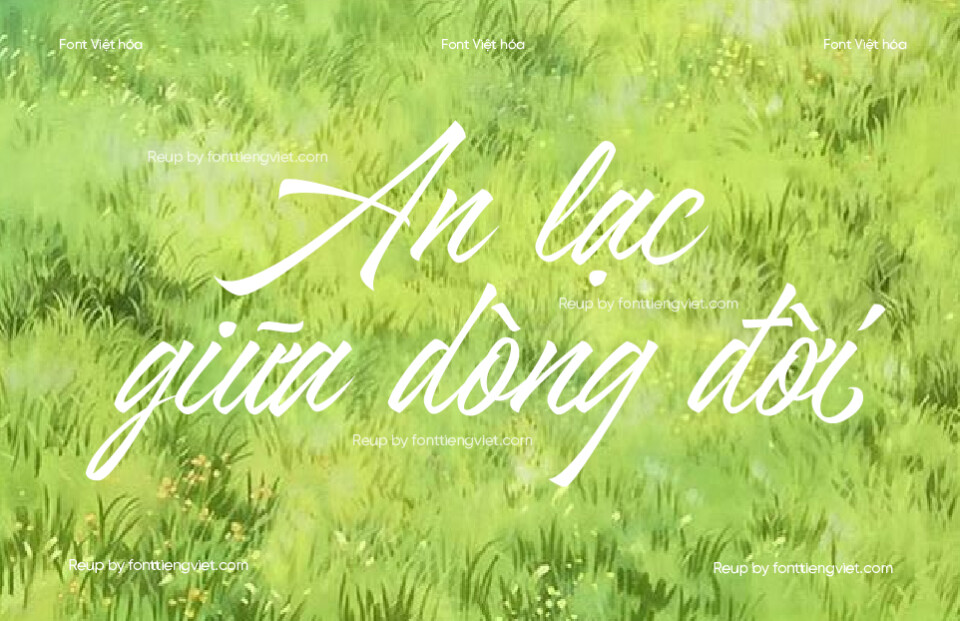
Khám Phá Nét Đẹp Tinh Tế Của Font Việt hóa UTM Azkia Trong Thiết Kế
Trong thế giới của typography và thiết kế đồ họa, việc lựa chọn một bộ phông chữ phù hợp có thể quyết định đến sự thành công của toàn bộ dự án. Font Chữ không chỉ là công cụ truyền tải thông điệp mà còn là linh hồn tạo nên phong cách. Trong số các lựa chọn đa dạng hiện nay, Font Việt hóa UTM Azkia nổi lên như một lựa chọn hàng đầu cho những ai tìm kiếm sự kết hợp giữa nét đẹp mềm mại, cổ điển nhưng vẫn rất hiện đại. Được phát triển và Việt hóa hoàn chỉnh, UTM Azkia đã nhanh chóng chiếm được cảm tình của cộng đồng designer Việt Nam, đặc biệt trong các lĩnh vực như thiết kế thiệp cưới, bao bì sản phẩm cao cấp, và nhận diện thương hiệu sang trọng. Bộ font này mang đến sự trau chuốt, tỉ mỉ mà ít phông chữ nào có thể sánh được.
Giới Thiệu Chi Tiết Về Font Việt hóa UTM Azkia và Đặc Điểm Nổi Bật
Font Việt hóa UTM Azkia thuộc nhóm font script hoặc brush script, nổi bật với các nét uốn lượn mềm mại, dứt khoát mô phỏng chữ viết tay thư pháp. Sự Việt hóa chuẩn mực là yếu tố then chốt giúp font này trở nên phổ biến, đảm bảo rằng mọi ký tự tiếng Việt, bao gồm các dấu câu và chữ cái có dấu, đều được hiển thị một cách hoàn hảo và tự nhiên nhất. Điều này giải quyết triệt để vấn đề lỗi phông thường gặp khi sử dụng các font quốc tế chưa được tối ưu cho tiếng Việt.
Điểm mạnh của UTM Azkia không chỉ nằm ở tính thẩm mỹ cao mà còn ở sự đa dạng trong cách thể hiện cảm xúc. Nó có thể được sử dụng để truyền tải sự lãng mạn, sự tinh tế, hoặc thậm chí là một chút phá cách, tùy thuộc vào cách bạn kết hợp nó với các yếu tố thiết kế khác. Các nét nối liền mạch và độ dày mỏng linh hoạt của nét chữ tạo nên một cảm giác rất “thủ công” và chân thực.
Khác Biệt Giữa UTM Azkia Gốc và Bản Việt Hóa
Bản gốc Azkia là một font chữ tuyệt đẹp, nhưng để sử dụng hiệu quả trong môi trường tiếng Việt, việc “Việt hóa” là bắt buộc. Nhóm Việt hóa UTM đã thực hiện công việc tỉ mỉ này, không chỉ thêm các ký tự dấu mà còn tinh chỉnh kerning và spacing để đảm bảo sự hài hòa tổng thể. Nhờ quá trình này, người dùng hoàn toàn có thể yên tâm sử dụng font này cho các tài liệu học tập, sách báo, hay các ấn phẩm in ấn đòi hỏi sự chính xác cao về mặt ngôn ngữ.
Việc sử dụng các font chữ đã được Việt hóa như Azkia giúp các bạn học sinh, sinh viên trong quá trình làm tiểu luận, thiết kế bài thuyết trình hoặc làm các dự án sáng tạo cá nhân có được sản phẩm chuyên nghiệp hơn. Thay vì dùng các font phổ thông, Azkia mang lại dấu ấn cá nhân rõ nét.
Ứng Dụng Đa Dạng Của UTM Azkia Trong Đời Sống Số và Thiết Kế
Font Việt hóa UTM Azkia không chỉ giới hạn trong các ấn phẩm in ấn mà còn rất được ưa chuộng trong lĩnh vực thiết kế website và thương mại điện tử. Với khả năng tương thích cao và vẻ ngoài thu hút, font này là lựa chọn lý tưởng cho các:
- Thiết kế Logo và Nhận Diện Thương Hiệu: Mang lại sự độc đáo, sang trọng cho các thương hiệu thời trang, mỹ phẩm, hoặc dịch vụ cao cấp.
- Thiệp Cưới và Lời Mời Sự Kiện: Tạo ra cảm giác lãng mạn, cá nhân hóa sâu sắc, rất phù hợp với các dịp lễ kỷ niệm quan trọng.
- Bao Bì Sản Phẩm: Giúp sản phẩm nổi bật trên kệ hàng, truyền tải thông điệp về chất lượng và sự tinh tế.
- Poster và Banner Quảng Cáo: Thu hút sự chú ý ngay lập tức nhờ vào độ nghệ thuật của nét chữ.
Việc Việt hóa hoàn chỉnh cũng là một lợi thế lớn, giúp các nội dung tiếng Việt được hiển thị chính xác, tránh các lỗi kỹ thuật làm giảm chất lượng nội dung. Đây là một điểm mà các nhà thiết kế nội dung và các chuyên gia SEO trường học cần lưu ý khi xây dựng website giáo dục.
Tóm lại, Font Việt hóa UTM Azkia là một tài sản vô giá đối với bất kỳ ai làm trong lĩnh vực thiết kế hay đơn giản là người yêu thích cái đẹp của chữ viết. Nó không chỉ mang lại tính thẩm mỹ cao mà còn giải quyết được vấn đề ngôn ngữ tiếng Việt một cách hoàn hảo. Từ những dự án học thuật của sinh viên, bài thi tốt nghiệp trung học, cho đến các chiến dịch marketing chuyên nghiệp, UTM Azkia đều có thể nâng tầm chất lượng sản phẩm. Việc đầu tư thời gian để tìm hiểu và sử dụng thành thạo bộ Font Chữ này chắc chắn sẽ mang lại nhiều lợi ích sáng tạo. Đừng ngần ngại tải về và trải nghiệm vẻ đẹp tinh tế của Font Việt hóa UTM Azkia ngay hôm nay để làm phong phú thêm bộ sưu tập font chữ cá nhân của bạn!